싸인은 단순한 이름의 표기가 아니라, 곧 나 자신을 상징하는 강력한 도구가 될 수 있어요. 우리가 사인을 할 때마다 자신만의 스타일과 개성을 담아내고, 이것이 반복되면 브랜드가 될 수도 있죠. 실제로 유명 아티스트나 기업가들은 싸인을 하나의 브랜드로 활용해 엄청난 가치를 만들어내고 있어요.
나이키의 '스우시' 로고처럼 단순한 기호도 브랜드가 되듯이, 나만의 독창적인 싸인을 만든다면 나를 대표하는 브랜드로 성장할 가능성이 충분해요. 싸인이 브랜드가 되는 원리를 이해하고, 효과적으로 활용하는 방법을 알아볼까요? 🔥
🖊 싸인의 정체성과 의미
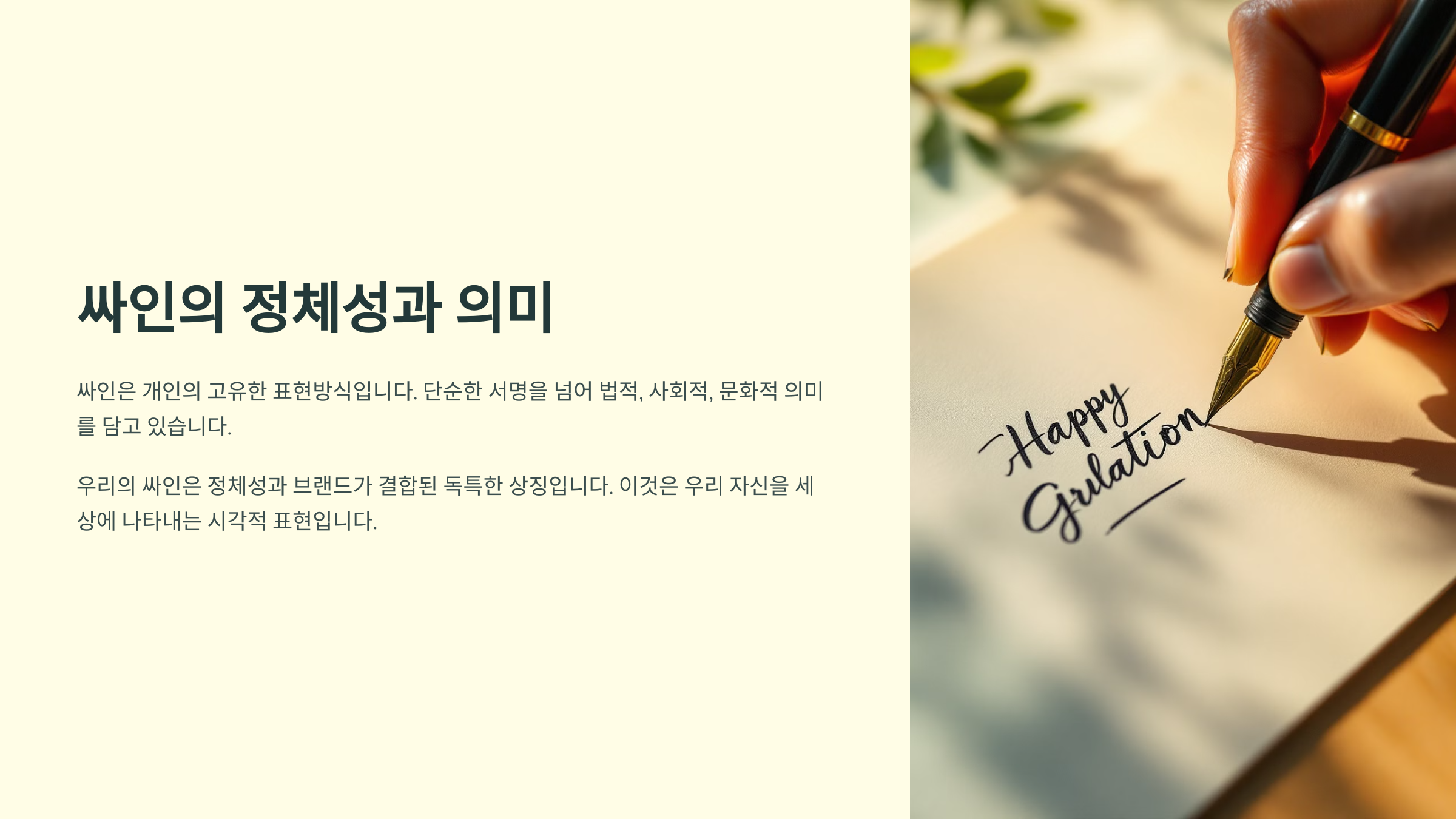
싸인은 단순한 이름이 아니라, 나의 정체성을 담아내는 중요한 요소예요. 싸인을 보면 그 사람의 성격, 개성, 심지어 직업까지도 엿볼 수 있어요. 예를 들어, 곧고 반듯한 싸인은 신뢰감을 주고, 독특한 필체의 싸인은 창의적인 느낌을 줘요.
싸인은 또한 나의 가치관과 철학을 상징하기도 해요. 유명한 화가 피카소는 싸인을 하나의 예술로 만들었고, 마이클 조던은 싸인을 통해 자신의 농구 실력과 브랜드를 각인시켰어요. 이렇게 싸인은 단순한 필체를 넘어 '나'라는 브랜드의 일부가 될 수 있어요.
✨ 유명인의 싸인 스타일 비교 ✨
이름 싸인 스타일 특징 마이클 조던 MJ + 점프맨 스포츠 브랜드와 연결된 시그니처 스티브 잡스 단순한 필기체 미니멀리즘 철학 반영 피카소 예술적 곡선 포함 싸인 자체가 예술 작품 싸인이 브랜드가 되기 위해선 반복적으로 사용되면서 사람들에게 익숙해져야 해요. 자주 노출될수록 싸인은 더욱 강력한 브랜드 요소가 될 수 있답니다. 😊
🚀 싸인이 브랜드가 되는 이유
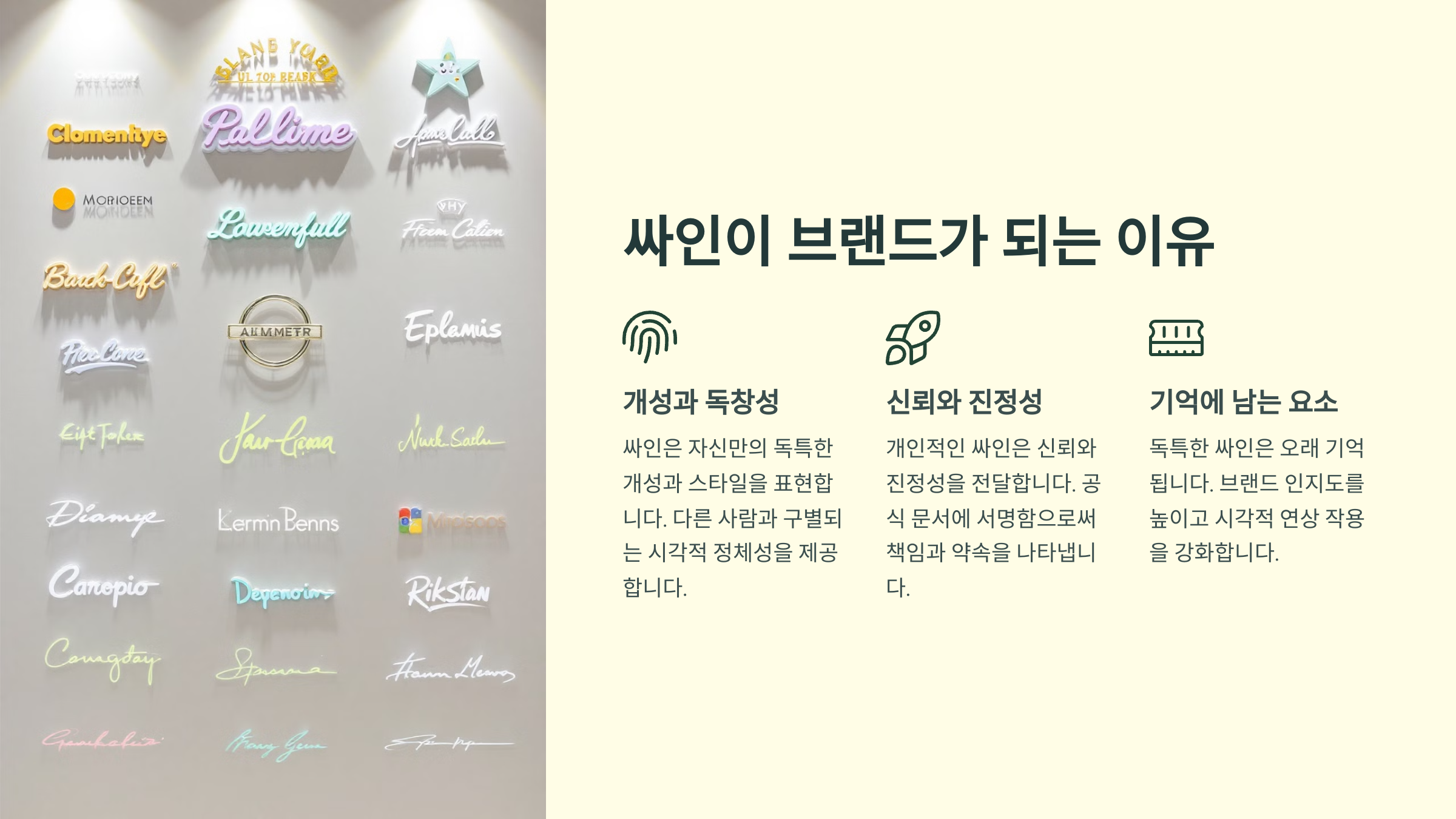
싸인은 단순한 서명이 아니라, 강력한 브랜드 자산이 될 수 있어요. 특히, 유명 인사나 아티스트, 기업가들이 자신의 싸인을 상표처럼 활용하는 경우가 많아요. 그렇다면 싸인이 브랜드가 될 수 있는 이유는 무엇일까요? 🤔
첫째, 싸인은 ‘개성’을 담고 있어요. 기업 로고처럼 독창적인 싸인은 사람들에게 쉽게 기억될 수 있어요. 예를 들어, 나이키의 ‘스우시’처럼 간단한 기호도 반복적으로 사용되면 강력한 브랜드가 되죠.
둘째, 싸인은 ‘신뢰’를 상징해요. 계약서에 싸인을 하면 법적 효력이 생기는 것처럼, 싸인은 권위와 신뢰를 부여하는 역할을 해요. 특히 유명인이 자신의 싸인을 제품에 새기면, 그것만으로도 큰 마케팅 효과를 볼 수 있답니다.
📌 싸인이 브랜드로 자리 잡는 3가지 이유 📌
요소 설명 예시 개성 싸인은 고유한 필체와 디자인으로 차별화될 수 있어요. 김연아의 사인, 나이키 스우시 신뢰 싸인은 공식적인 문서나 제품에 사용되며 신뢰를 더해요. 애플 창업자 스티브 잡스의 싸인 희소성 한정판 싸인은 수집 가치가 높아지고 브랜드 가치를 상승시켜요. 마이클 조던 싸인 농구공 내가 생각했을 때, 싸인은 단순한 서명이 아니라 자신을 대표하는 하나의 '상징'이에요. 싸인이 꾸준히 활용되면 사람들은 그 싸인을 볼 때마다 당신을 떠올리게 되죠. 😊
🌟 유명인의 싸인과 브랜드 사례
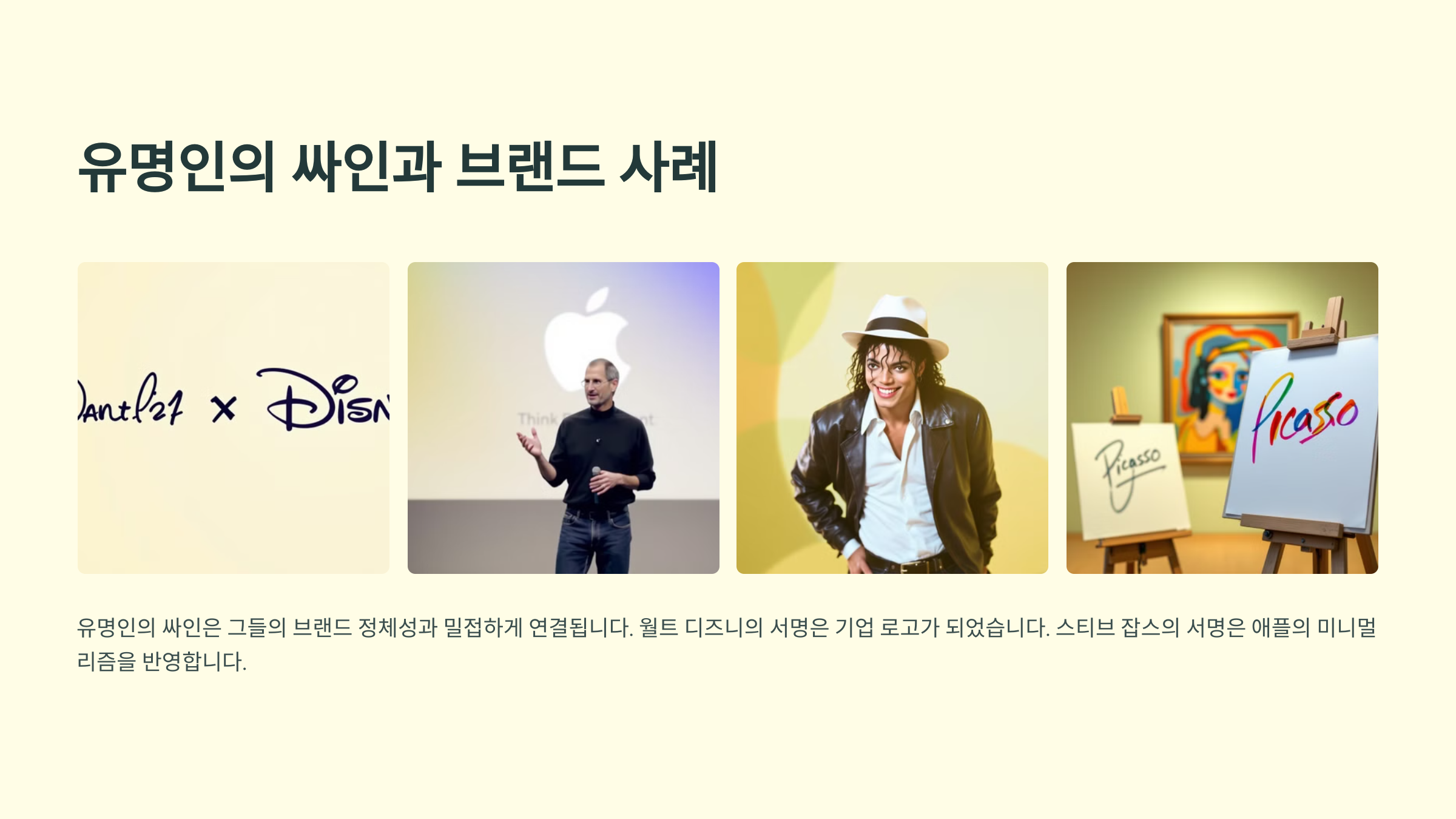
싸인을 브랜드로 활용한 유명한 사례들은 많아요. 특히 스포츠 스타, 아티스트, 기업가들은 싸인을 통해 자신의 가치를 높이고 강력한 브랜드를 구축했죠. 그들의 싸인은 단순한 이름이 아니라, 곧 상징이 되어 엄청난 가치를 지니게 되었어요.
대표적인 예로 마이클 조던의 싸인을 들 수 있어요. 그는 농구 역사상 최고의 선수 중 한 명으로, 그의 싸인이 들어간 운동화, 포스터, 농구공은 엄청난 가격에 거래돼요. 조던 브랜드 자체도 그의 싸인과 연결되어 있죠.
또 다른 예로, 스티브 잡스의 싸인이 들어간 애플 제품이 있어요. 잡스의 싸인이 새겨진 맥북이나 아이폰 박스는 희소성이 높아 수집가들에게 큰 가치를 지니죠. 단순한 서명이 아니라, 잡스의 혁신 정신을 담은 브랜드가 되었어요.
🔥 싸인으로 브랜드 가치를 높인 사례 🔥
이름 싸인 특징 브랜드 가치 마이클 조던 간결한 필기체 + 점프맨 로고 수집가들에게 수천만 원 가치 스티브 잡스 미니멀한 서명 스타일 애플 제품과 함께 희소 가치 상승 엘비스 프레슬리 화려한 필기체 스타일 음악 팬들에게 특별한 의미 이처럼 유명인의 싸인은 단순한 서명이 아니라, 강력한 브랜드 자산이 될 수 있어요. 싸인이 반복적으로 사용되면 사람들은 그 싸인만 봐도 브랜드를 떠올리게 되죠. 😉
그렇다면, 우리도 나만의 싸인을 만들어 브랜드로 활용할 수 있을까요? 다음 섹션에서 나만의 싸인을 만드는 방법을 알아볼까요? ✍
✍ 나만의 싸인 만드는 방법
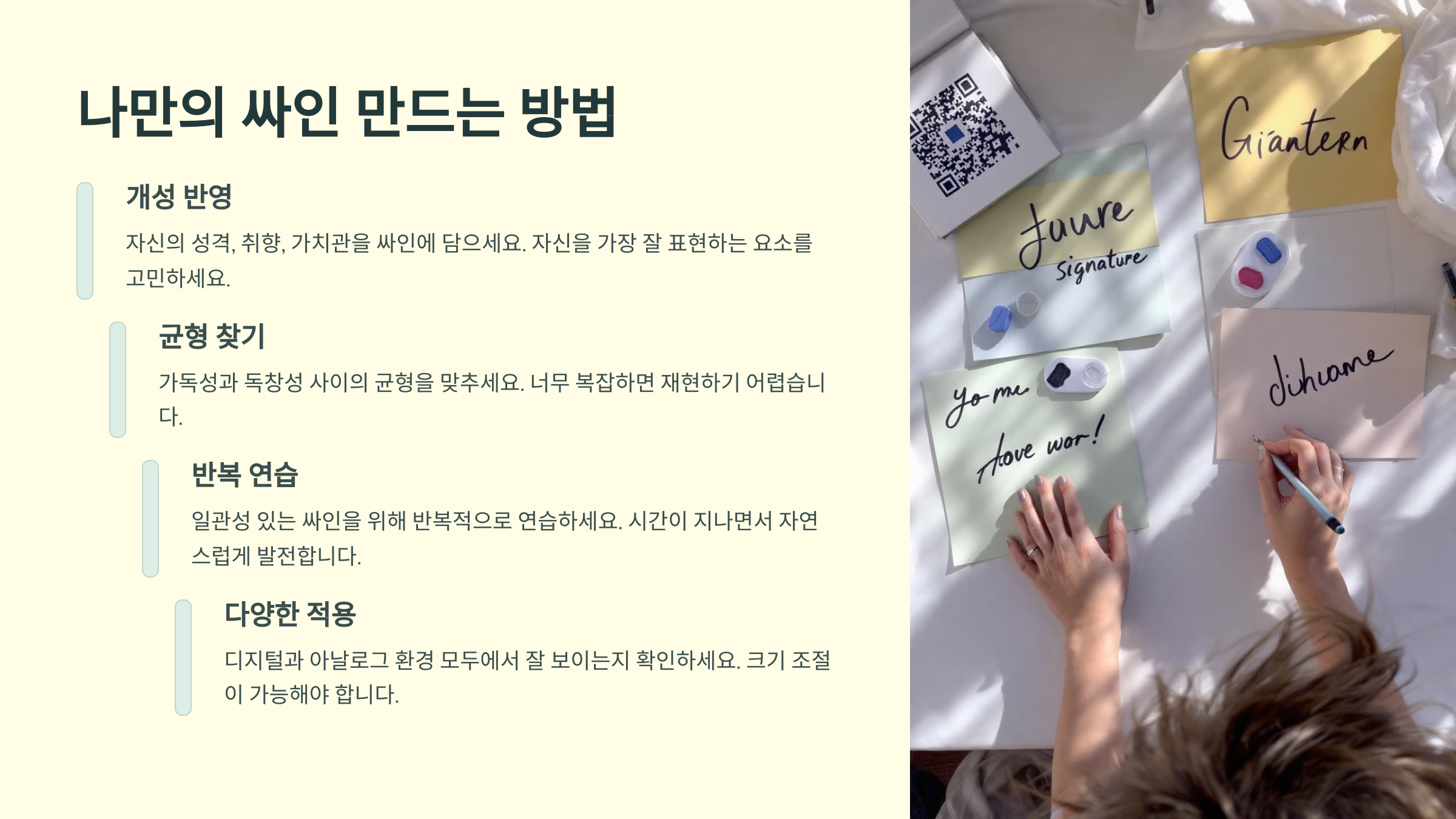
나만의 싸인을 만든다는 건 단순한 필체 연습이 아니라, 나를 대표하는 ‘브랜드’를 구축하는 과정이에요. 싸인은 한 번 정하면 꾸준히 사용해야 브랜드로 자리 잡을 수 있답니다. 그렇다면, 어떻게 하면 멋지고 독창적인 싸인을 만들 수 있을까요? 🤔
먼저, 자신이 원하는 싸인의 스타일을 정해야 해요. 클래식한 필기체 스타일, 미니멀한 디자인, 혹은 예술적인 감각이 들어간 스타일 등 다양한 선택지가 있어요. 유명인들의 싸인을 참고하면서 자신만의 개성을 살려보세요!
다음으로, 여러 번 연습하면서 자신에게 맞는 싸인을 찾아야 해요. 처음에는 여러 스타일을 시도해 보고, 가장 자연스럽고 멋진 형태를 선택하면 돼요. 싸인은 빠르게 써야 할 때도 많기 때문에 너무 복잡한 디자인보다는 간결하면서도 개성 있는 싸인이 좋아요.
🖊 나만의 싸인을 만드는 5단계 🖊
단계 설명 1. 스타일 결정 클래식, 미니멀, 예술적 스타일 중 선택 2. 이니셜 활용 이름의 첫 글자를 강조하는 디자인 고려 3. 반복 연습 자연스럽게 쓸 수 있도록 연습 4. 독창적인 요소 추가 특징적인 곡선, 기호, 심볼 활용 5. 디지털화 스캔 후 디지털 파일로 변환하여 활용 싸인을 만들 때 중요한 점은 ‘일관성’이에요. 한 번 정한 싸인은 모든 곳에서 동일하게 사용하는 것이 중요해요. 그래야 싸인이 브랜드로 자리 잡고, 사람들에게 익숙해질 수 있어요.
자, 이제 싸인을 만들었으니, 이 싸인을 어떻게 활용하면 브랜드 가치를 높일 수 있을까요? 다음 섹션에서 알아봐요! 🚀
💡 싸인을 활용한 마케팅 전략
싸인은 나만의 브랜드를 강화하는 데 유용한 도구가 될 수 있어요. 유명인들이 자신의 싸인을 제품이나 광고에 활용하는 것처럼, 우리도 싸인을 마케팅에 접목하면 강한 인상을 남길 수 있답니다. 😃
예를 들어, 자신의 싸인을 로고처럼 활용하는 방법이 있어요. 개인 브랜드를 운영하는 사람이라면 명함, 웹사이트, 상품 패키지 등에 싸인을 넣어보세요. 일관되게 사용하면 브랜드 아이덴티티를 확립하는 데 도움이 돼요.
또한 한정판 제품이나 콘텐츠에 싸인을 추가하면 희소성을 높일 수 있어요. 싸인이 들어간 한정판 책, 포스터, 의류, 액세서리 등은 더욱 특별한 가치를 가지게 되죠.
📢 싸인을 활용한 마케팅 아이디어 📢
마케팅 방법 활용 예시 로고처럼 활용 명함, 웹사이트, 소셜미디어 배너에 적용 한정판 상품 제작 싸인이 들어간 굿즈, 포스터, 책 판매 SNS에서 브랜드 강화 싸인을 활용한 프로필 이미지, 콘텐츠 제작 고객과의 소통 싸인이 들어간 편지, 이벤트 사인회 개최 싸인을 브랜드화하면 고객과의 신뢰도를 높일 수 있어요. 싸인이 들어간 콘텐츠는 더욱 개인적인 느낌을 주기 때문에, 팬이나 고객과의 관계를 더욱 돈독하게 만들 수 있답니다. 😉
이제 싸인을 보호하고 법적으로 안전하게 활용하는 방법을 알아볼까요? ⚖
⚖ 싸인의 법적 보호와 저작권
싸인은 단순한 필체가 아니라, 나만의 브랜드 자산이 될 수 있기 때문에 법적으로 보호하는 것이 중요해요. 유명인들의 싸인은 하나의 ‘상표’처럼 활용되며, 이를 보호하기 위해 저작권이나 상표권을 등록하는 경우도 많아요.
만약 나만의 싸인을 브랜드 로고나 상품에 활용하고 싶다면, 상표 등록을 고려해보는 것이 좋아요. 특히, 사업을 운영하거나 제품을 판매할 계획이라면, 싸인을 상표로 등록해 두면 법적으로 보호받을 수 있어요.
또한, 싸인이 유명해지면 위조되거나 도용될 가능성이 높아지기 때문에 저작권 보호도 필요해요. 자신의 싸인을 디지털 파일로 변환하여 저작권 등록을 해두면, 법적 분쟁이 발생했을 때 유리한 입장을 가질 수 있답니다.
📜 싸인을 법적으로 보호하는 방법 📜
보호 방법 설명 상표권 등록 싸인을 브랜드 로고로 사용한다면 상표 등록 필수 저작권 등록 싸인이 예술적 요소를 포함한다면 저작권 등록 가능 위조 방지 디지털 워터마크나 특수 디자인을 적용 법적 대응 무단 도용 시 변호사 상담 후 법적 조치 싸인을 상표나 저작권으로 보호하면, 다른 사람이 무단으로 사용하거나 위조하는 것을 방지할 수 있어요. 특히, 자신만의 브랜드를 구축하는 과정에서 법적 보호는 필수적인 요소랍니다. 😊
이제 싸인과 관련된 궁금증을 해결해 줄 FAQ를 살펴볼까요? 💬
Q1. 싸인을 브랜드로 만들기 위해 꼭 상표 등록을 해야 하나요?
A1. 꼭 필요한 것은 아니지만, 상표 등록을 하면 법적으로 보호받을 수 있어요. 특히 제품이나 서비스를 운영하는 경우, 싸인을 브랜드 로고처럼 활용할 계획이라면 등록하는 것이 좋습니다.
Q2. 싸인을 바꿔도 되나요?
A2. 싸인을 변경할 수 있지만, 브랜드로 자리 잡은 후 바꾸면 혼란이 생길 수 있어요. 한 번 정한 싸인은 일관되게 사용하는 것이 인지도를 높이는 데 도움이 됩니다.
Q3. 유명인의 싸인을 따라 해도 되나요?
A3. 유명인의 싸인을 무단으로 사용하는 것은 법적으로 문제가 될 수 있어요. 특히 상업적 목적으로 사용할 경우, 저작권이나 상표권 침해로 법적 분쟁이 발생할 수 있습니다.
Q4. 싸인을 디지털 파일로 만들려면 어떻게 해야 하나요?
A4. 싸인을 종이에 작성한 후 스캔하거나, 태블릿을 이용해 직접 디지털 싸인을 만들 수 있어요. 이후 PNG 또는 벡터 파일 형식으로 저장하면 로고처럼 활용할 수 있습니다.
Q6. 내 싸인이 위조될 위험이 있을까요?
A6. 싸인이 유명해지면 위조될 가능성이 있어요. 이를 방지하기 위해 상표 등록을 하거나, 디지털 워터마크를 추가하는 방법이 있습니다.
Q7. 싸인에도 저작권이 적용되나요?
A7. 일반적인 서명은 저작권 보호 대상이 아니지만, 예술적인 요소가 포함된 독창적인 디자인이라면 저작권 보호를 받을 수 있습니다.
Q8. 싸인을 쉽게 연습하는 방법이 있을까요?
A8. 여러 스타일을 시도해 보면서 가장 자연스럽고 멋진 형태를 찾는 것이 중요해요. 연습할 때는 다양한 필기구를 사용해 보고, 반복적으로 써보면서 손에 익히는 것이 좋아요.